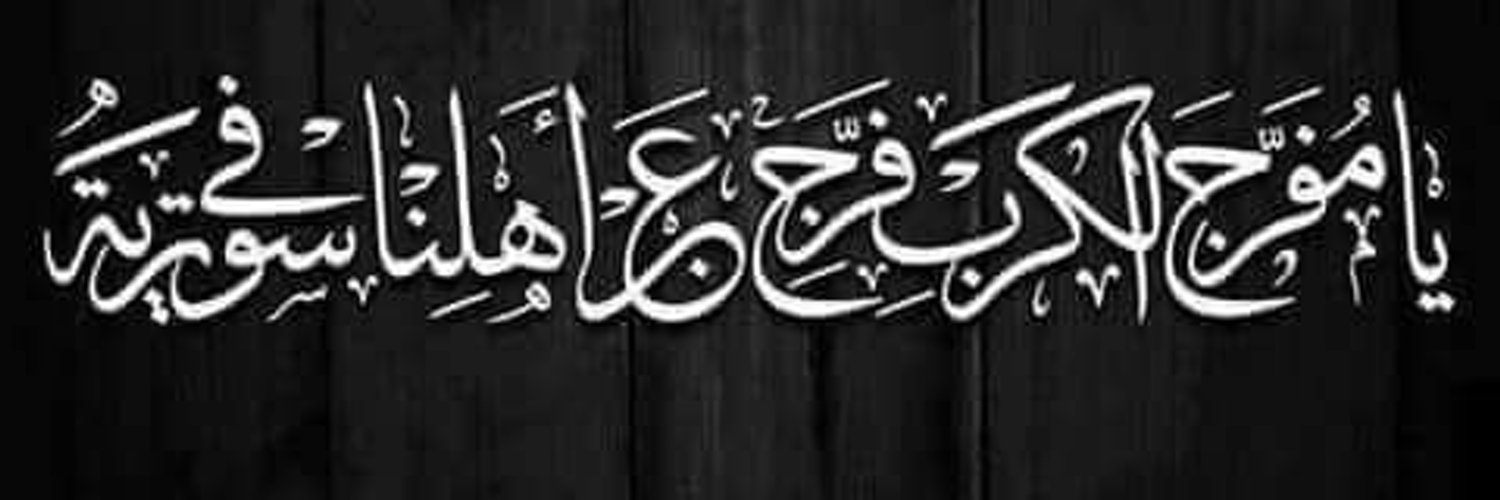
буквы араб. Вы когда-нибудь задумывались, как толпа добавляет отличительные буквы в своих социальных сетях? Если вы работали в Instagram, Twitter, Facebook, WhatsApp или Tik Tok, вы знаете, что у вас не так много альтернатив, когда дело доходит до настройки текстов песен с момента прохождения биографии, комментариев, подписей и т. д. иметь шрифт по умолчанию.
Нет параметров для настройки Тип букв, шрифты, символы и Символы и измените их, чтобы сделать его более эстетичным, в соответствии с вашими предпочтениями. Но не волнуйтесь! Вы все еще можете подать заявку Арабские буквы приятно и интересно благодаря этому преобразователь.
Используйте арабские буквы, С этим конвертер текстов песен вы можете установить необычные буквы, шрифты, символы и символы для своих заголовков в социальных сетях (Instagram, TikTok .
Пришло время заняться чем-то другим, тебе не кажется? Настройте биографию своего профиля или, возможно, улучшите части подписей к фотографиям и видео, которые вы публикуете. Преобразуйте обычный текст в разные стили Арабские буквы, например шрифты для татуировок, каллиграфические шрифты, веб-скрипт, курсив, письменные источники вручную, специальные символы, буквы, шрифты, гарнитуры, символы и символы или художественные.
В различных социальных сетях используется шрифт, который лучше всего соответствует общему дизайну системы. Это часть необходимого единообразия для визуального комфорта потребителей, просматривающих эти платформы.
Оказывается, есть способ получить оригинальные письма скопировать и вставить которые на самом деле являются единичными символами, а также emojis и другие символы. На практике они отображаются как адаптированные шрифты, но технически обозначаются как Символы Юникода.
Арабские буквы для копирования и вставки. Мы можем резюмировать, что с конвертером букв вы на самом деле не получаете сами шрифты, поскольку они являются символами Unicode, эти коды могут иногда менять в зависимости от мобильных устройств.
Это не означает, что этот механизм неисправен, это означает, что шрифт, выбранный для использования на сайте, не поддерживает этот символ. Но есть набор персонажей, которые, если они соответствуют дизайну и стилю, как они есть:
→ Код Unicode: что это такое?
Что такое Юникод?
Unicode был разработан для решить проблему, вызванную огромным существованием кодовых наборов. С самого начала программирования разработчики использовали свои языки, поэтому передача текста с одного ПК на другой часто приводила к потере информации.
Unicode приложил огромные усилия в 80-х годах, чтобы создать набор уникальных персонажей это охватывает всю систему письма.
El Стандарт Unicode может отображать шрифты и символы сотрудники на любом языке; включая смайлики, которые также являются текстовыми знаками.
Итак, с этим конвертером Арабские буквы вы не создаете шрифты, но Символы Unicode что вы можете использовать в Instagram, Twitter, Pinterest, Facebook, Tumblr, WhatsApp, TikTok… Когда вы найдете стиль шрифта, который вам больше всего нравится, вам просто нужно скопировать и вставить его туда, где он вам больше всего нравится.
➕ Текстовые шрифты
Первый 128 Символы списка Unicode являются наиболее часто используемыми и известны как алфавит. ASCII. Алфавит ASCII содержит буквы, десятичные цифры, знаки препинания и некоторые специальные символы.
Тем не менее, ASCII не обращается к знакам с диакритическими знаками, вопросительным знакам или некоторым другим символам (математическим, греческие буквы,…) Это верно в разных контекстах.
В качестве решения этих проблем, начиная с 1991 года, во всем мире было согласовано использование правила Unicode, которое представляет собой большую таблицу, где в настоящее время
La Таблица Unicode они связывают глиф (рисунок) с каждым из символов, например, знаменитый Arial или Times New Roman являются типографскими шрифтами. Поэтому текст, символы и декоративные знаки, которые вы видите в социальных сетях, являются Символы Unicode, которые вы можете скопировать и вставить в Instagram, TikTok, Twitter, Facebook или WhatsApp.
Генератор 🔥 арабских букв
Мукаддима — «библиографическая карточка» арабского сочинения, как правило, занимала унванный разворот и редко выходила за его рамки. Необходимость разместить «библиографическую карточку» таким образом, чтобы ее можно было охватить взглядом, вероятно, была причиной того, что текст сочинения начинался чаще всего на оборотной стороне первого листа, на что указал в своей работе Вал. В. Полосин [42, с. 77 и сл.].
Заключение. Художественное оформление арабской рукописной книги
О многообразии арабографичной рукописной традиции написано достаточно.